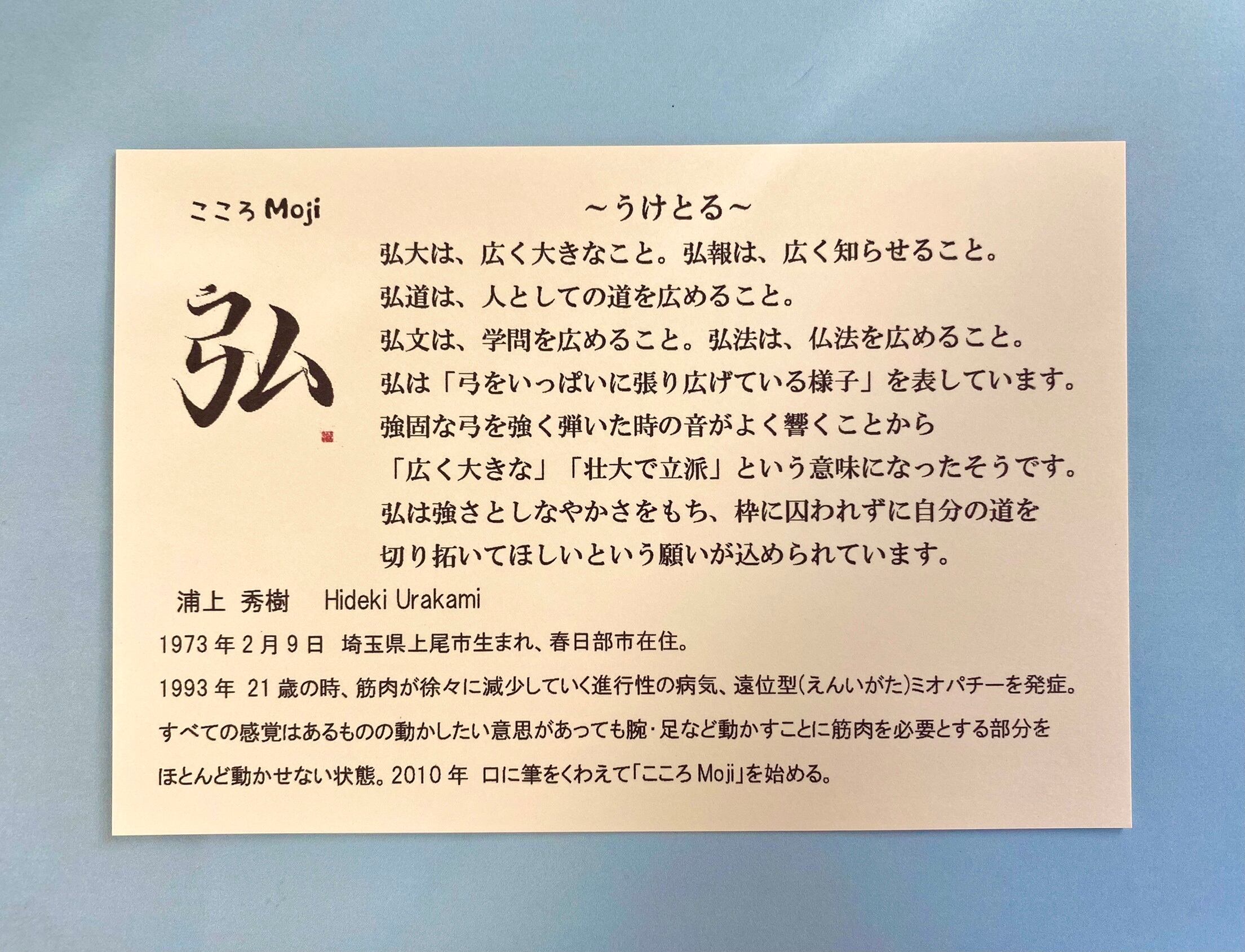
『弘』~うけとる~
弘大は、広く大きなこと。
弘報は、広く知らせること。
弘道は、人としての道を広めること。
弘文は、学問を広めること。
弘法は、仏法を広めること。
弘は「弓をいっぱいに張り広げている様子」を表しています。
強固な弓を強く弾いた時の音がよく響くことから「広く大きな」「壮大で立派」という意味になったそうです。弘は強さとしなやかさをもち、枠に囚われずに自分の道を切り拓いてほしいという願いが込められています。